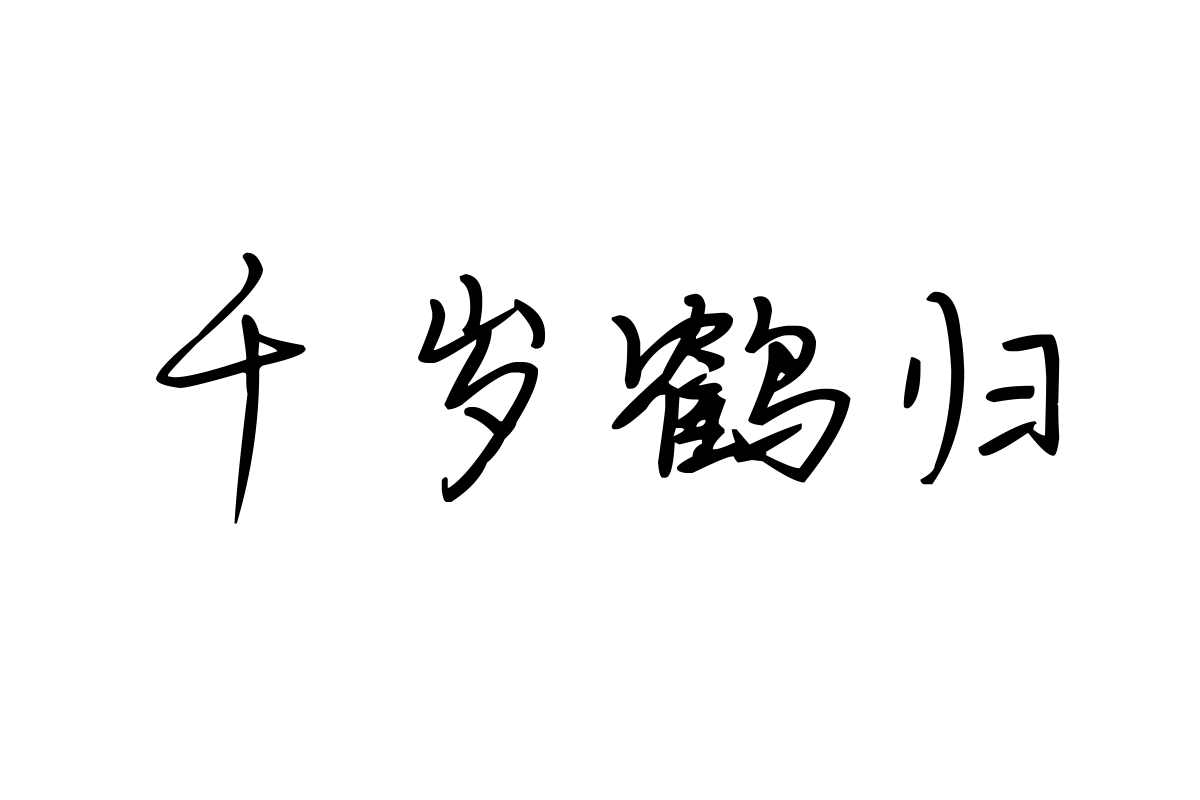
米开青春日记是一款由小米公司开发的手机应用,提供了多种字体供用户选择。以下是该应用的一些字体介绍:
1. 米开青体:这是一种简洁大方的字体,适合用于标题和正文。其笔画粗细适中,易于阅读。
2. 米开黑体:这是一种经典的中文字体,适用于需要强调的文字。其笔画粗犷,给人一种强烈的视觉冲击。
3. 米开楷体:这是一种较为规整的中文字体,适用于书写文字。其笔画清晰,易于模仿。
4. 米开行书:这是一种较为流畅的中文字体,适用于需要表达情感的文字。其笔画连绵,给人一种飘逸的感觉。
5. 米开宋体:这是一种传统的中文字体,适用于需要展现文化底蕴的文字。其笔画圆润,给人一种古朴的感觉。
6. 米开草书:这是一种较为自由的中文字体,适用于需要表现个性的文字。其笔画自由奔放,给人一种狂放不羁的感觉。
以上只是部分字体的介绍,米开青春日记还提供了其他多种字体供用户选择,以满足不同场景的需求。
米开青春日记